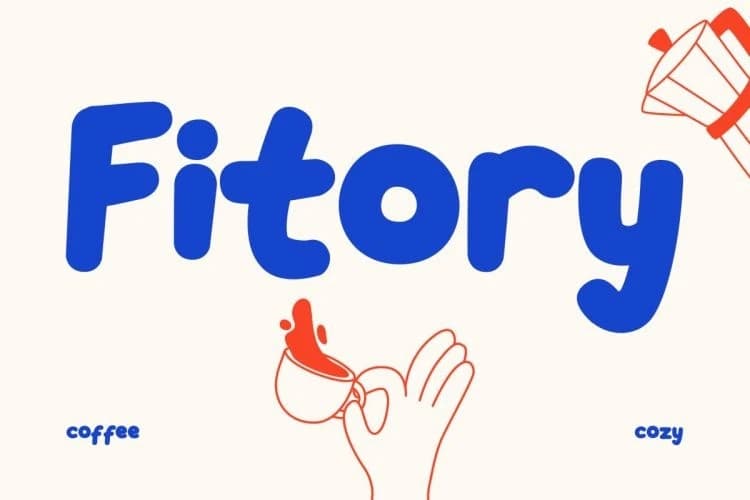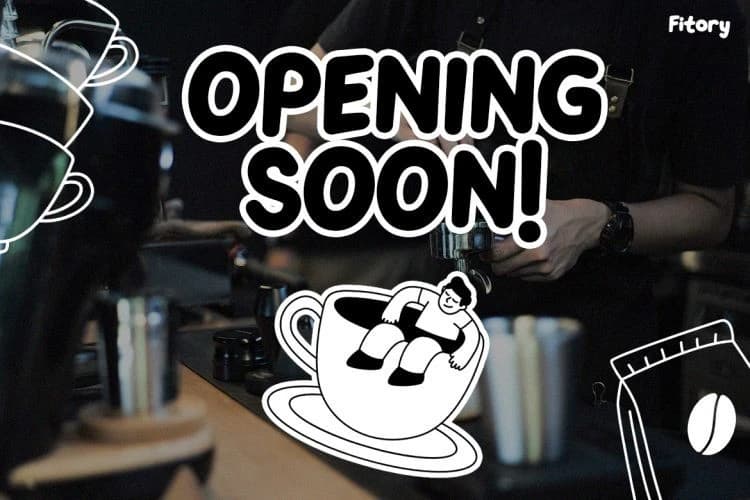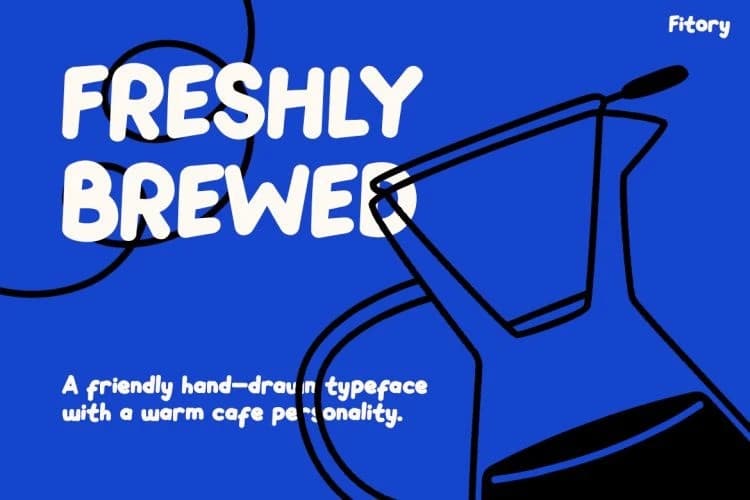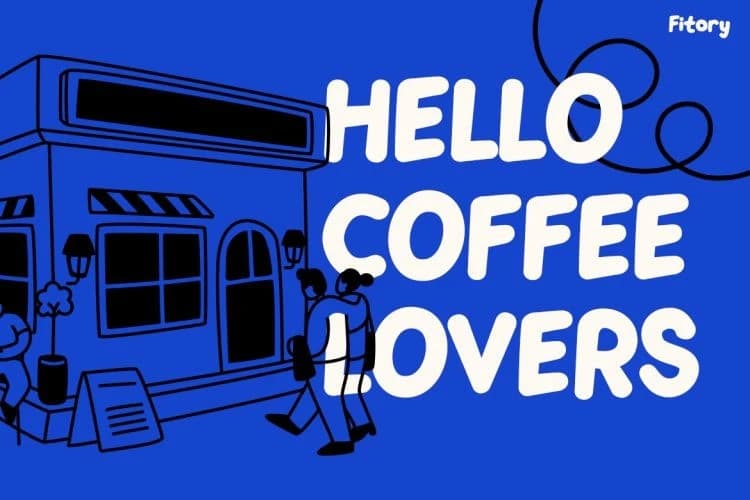
Fitory Playful Font
Fitory Playful Font, herhangi bir tasarıma sıcaklık ve neşe katan çekici, el ile çizilmiş bir yazı tipidir. Yuvarlak hatları ve yumuşak eğrileri samimi bir görünüm yaratır. Ayrıca, oyuncu harf biçimleri canlı ve ifadeli bir his verir.
Fitory Playful Font, her tasarıma sıcaklık ve neşe katan çekici, elle çizilmiş bir yazı tipidir. Köşeleri yuvarlak ve yumuşak eğrileri dostça bir görünüm yaratır. Ayrıca, oyuncu harf biçimleri canlı ve ifade dolu bir his verir.